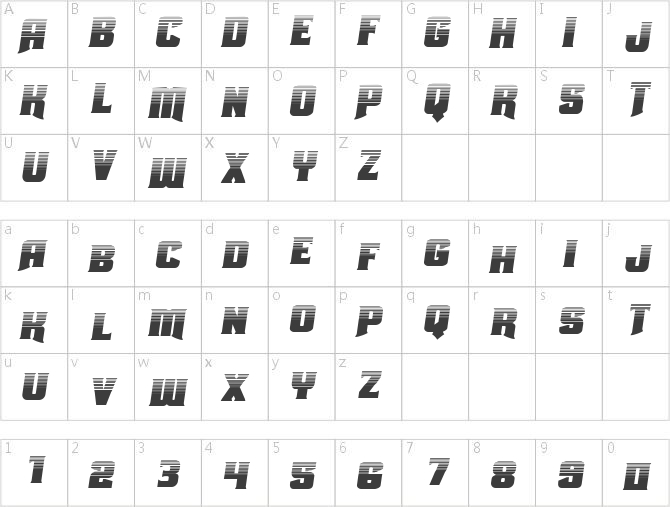
Union Gray Halftone Semi-Italic
Union Gray Halftone Semi-Italic介绍
Union Gray Halftone Semi-Italic字体字库是一款让人赏心悦目、百看不厌的英文字体,适合各类广告和产品包装设计应用,字体大小0.07MB,格式为ttf字体,上传用户是漫步云端,作者/版权方为未知